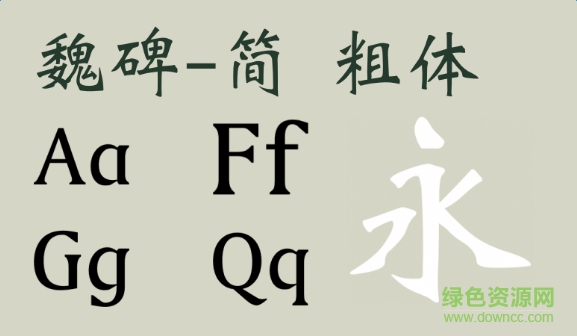
weibei sc bold(魏碑簡粗體)是一款形體端正的魏碑字體,字形瘦勁有力,筆法跳躍,流暢灑脫,看上去莊重嚴(yán)肅,常常用于藝術(shù)設(shè)計(jì)方面!
魏碑風(fēng)格多樣,樸拙險(xiǎn)峻,舒暢流麗。極有名的如《鄭文公碑》、《張猛龍碑》、《高貞碑》、《元懷墓志》及《張玄墓志》,已開隋、唐楷書法則的先河。清代中期倡導(dǎo)“尊碑抑帖”,沖破“館閣體”的束縛,碑學(xué)興起,書風(fēng)為之一變。魏碑上承漢隸傳統(tǒng),下啟唐楷新風(fēng),為現(xiàn)代漢字的結(jié)體、筆法奠定了堅(jiān)實(shí)的基礎(chǔ)。但有許多摩崖石刻,并不是先行書丹上石,而是直接在石面上雕鑿的,臨寫時(shí)要注意不使刀痕夸張,免生習(xí)氣。